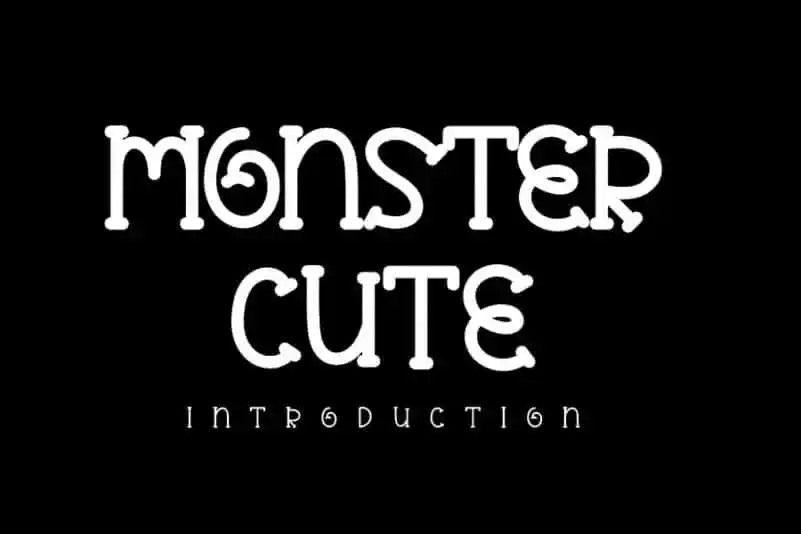
Monster Cute Display Font – Fonte Grátis
Monster Cute Display Font
A Monster Cute Display Font é uma fonte cuidadosamente criada que transmite a sensação de uma escrita a mão autêntica, mas mantém seu estilo formal do tipo chineses enquanto parece fresco e atual. Esta fonte exibida em grande destaca-se por sua versatilidade, capaz de capturar a imaginação para uma variedade de ideias criativas. Seja ela utilizada em cartões de visita ou títulos, esta elegante fonte é perfeita para projetos impressos que exigem um toque casual e moderno. Ideal tanto para designers profissionais quanto para entusiastas da design, a Monster Cute Display Font oferece uma maneira única de destacar seus trabalhos gráficos. Engajando-se nos detalhes, ela se adapta perfeitamente às necessidades dos projetos que vão além do básico, trazendo um toque único e inovador ao seu trabalho.